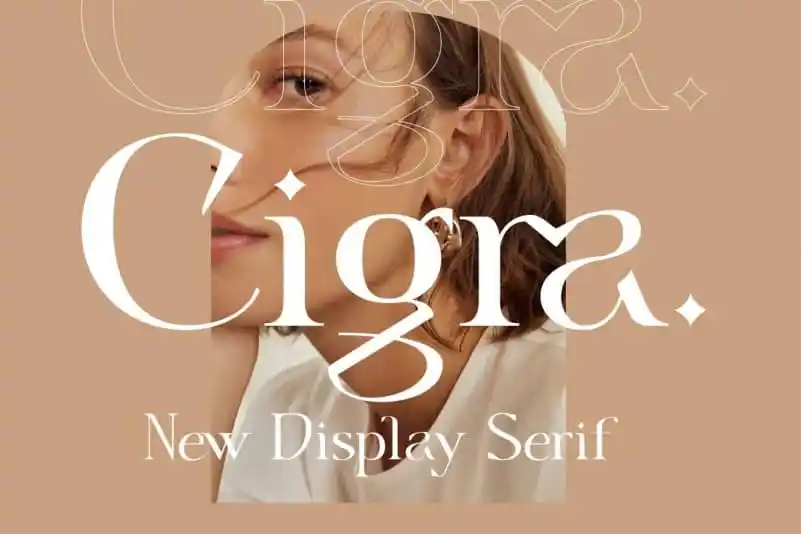
A Cigra Serif é uma fonte serif que oferece alternativas, ligaturas e suporte a múltiplas línguas. Desenhada pelo Identitype, esta font se destaca por suas curvas elaboradas e formas únicas, tornando-a perfeita para cabeçalhos, logos e convites de casamento. Suas linhas elegantes garantem que essa font seja atraente e cativante, certamente chamando atenção do público. Se você está procurando uma fonte sofisticada para dar um toque especial aos seus projetos, a Cigra é uma escolha ótima.